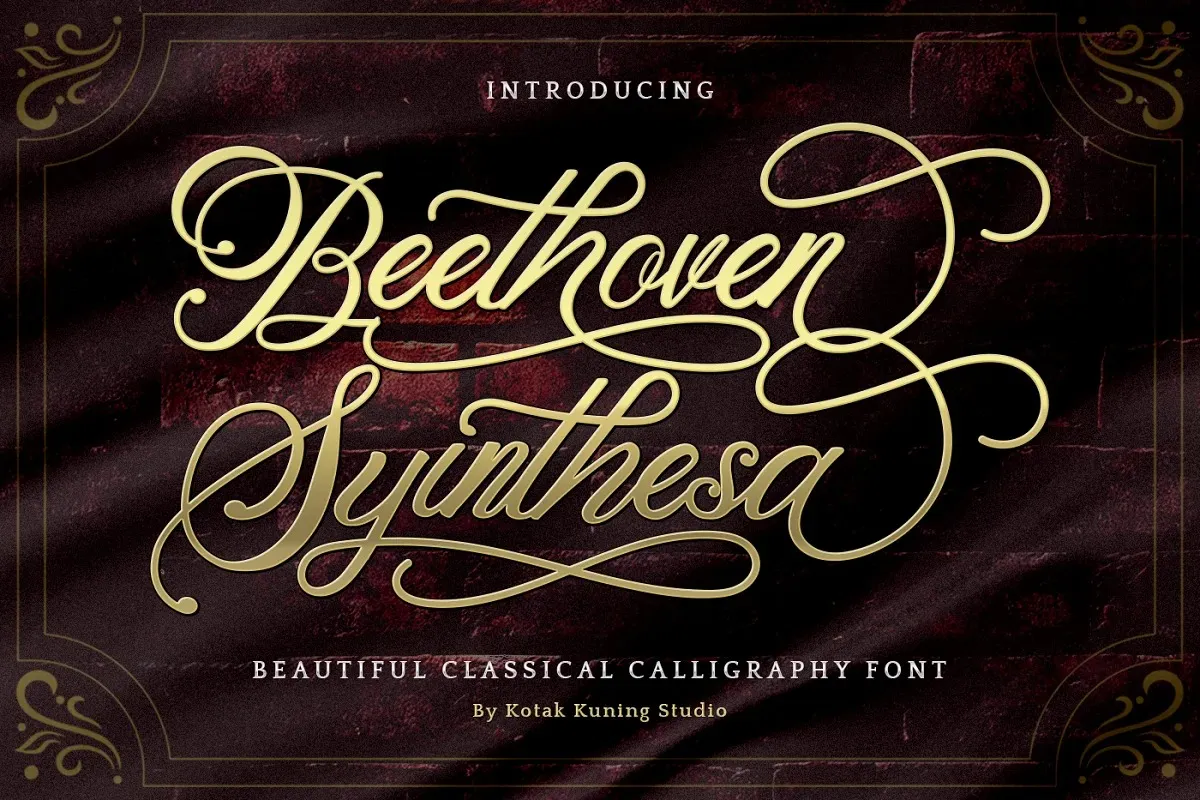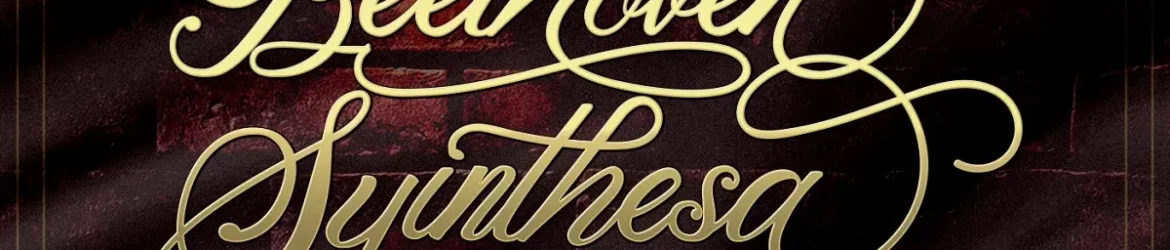
Beethoven Syinthesa Font – Download Grátis
A Beethoven Syinthesa Font é uma fonte script que nasceu de caracteres escritos a mão naquele famoso tom de papel com uma ponta firme e caneca de tinta grossa. Inspirada no estilo original e natural dos escritos humanizados, ela se destaca para tornar declarações elegantes e estilosas – ou para adicionar um toque de classe aos seus projetos gráficos. Com uma diversidade incrível de ligaturas naturais e caracteres alternativos presentes em suas características OpenType, a Beethoven Syinthesa está feita para fazer seu design soar como o natural da escrita à mão. Esta fonte oferece um nível de realismo que torna-a perfeita para aqueles projetos que precisam de uma sensação genuína e natural do papel. Revelando os detalhes profundos dos textos, essa fonte é ideal para designers buscando dar vida a suas criações com estilo e sofisticação. O resultado final é um design visual que reflete a autenticidade da mão humana em cada letra, tornando-se uma escolha valiosa para aqueles desejosos de criar algo único e imediatamente reconhecível.